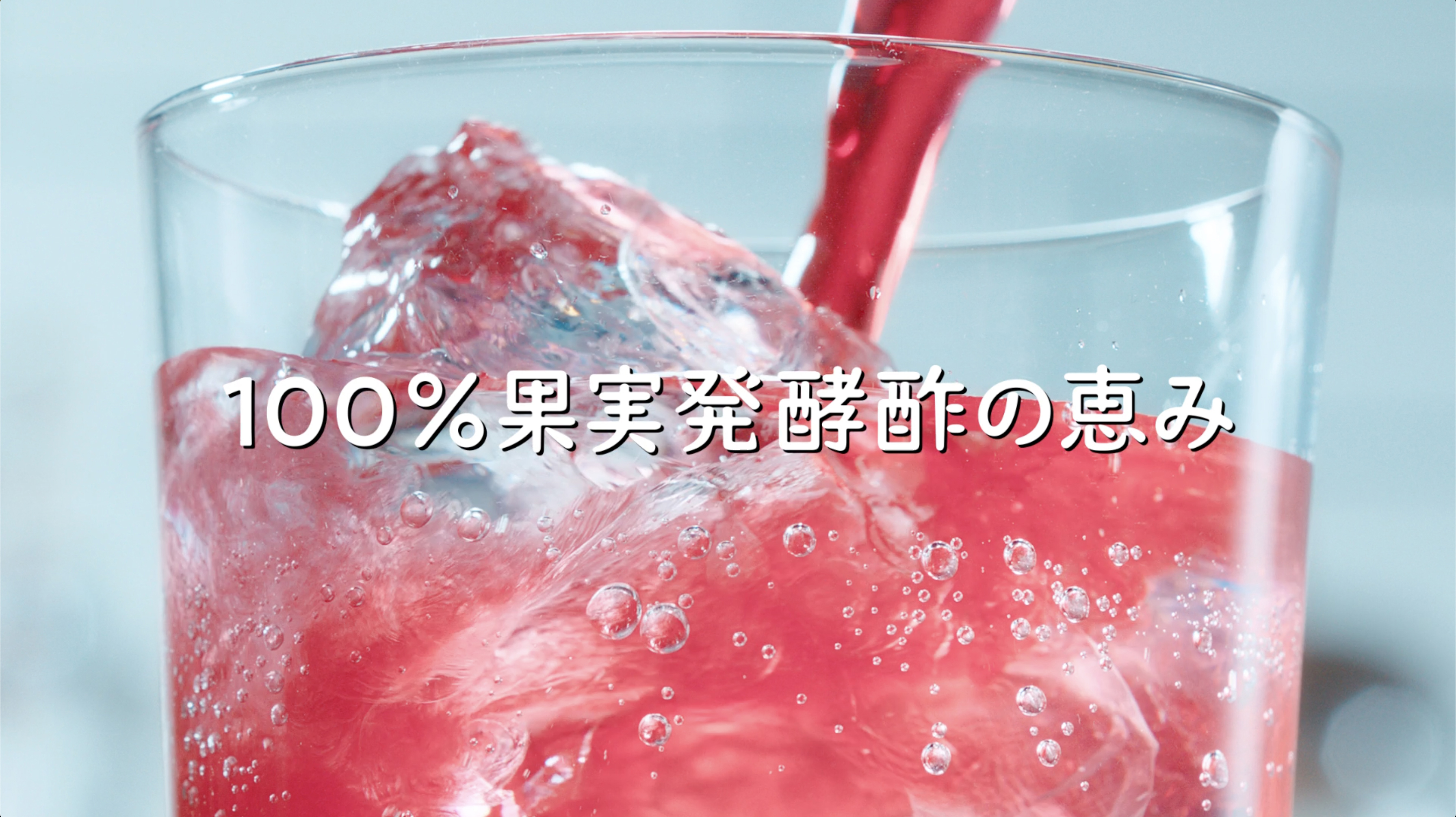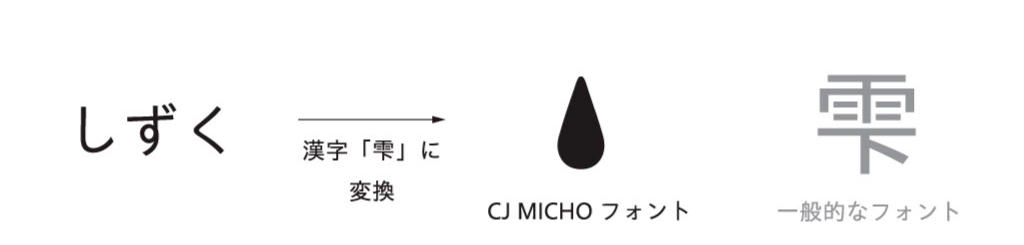
パッケージや広告デザインの
自由度が上がった!
ブランドの世界観を表現する
135文字のオリジナルフォント
韓国食品事業を展開するCJ FOODS JAPANのビネガードリンクブランド「美酢(ミチョ)」は、リブランディングプロジェクトの一環としてクリエイティブデザインを刷新し、2022年にオリジナルフォント「CJ MICHO」をモリサワと共同開発した。同社にとって初となるオリジナルフォントの制作過程、フォントの要件などについて、マーケティング部の担当者に伺った。
日本進出から10年を機にリブランディングのプロジェクトを始動
美酢は「100%果実発酵酢から作ったビネガードリンク」という、従来のお酢飲料とは全く異なるコンセプトで2011年に日本市場に進出した。それまで「味は二の次で、健康のために我慢して飲む」ものであり、中高年の男性が主な購買層だったお酢飲料のイメージを覆し、健康や美容を意識する若い女性を中心に支持を拡大。販路の多様化や積極的なマーケティング活動も、美酢ブランドの認知向上につながっている。
CJ FOODS JAPANは、日本で美酢の販売を開始してから10年が経過したのを機に、リブランディングのプロジェクトを始動。ターゲットである若年層に、身近さや美容面のベネフィットをさらに訴求するため、クリエイティブを刷新することになった。「改革というと大げさですが、今の時代に即したベストなデザインにしていこうという趣旨です」と、美酢のパッケージ、広告などのデザインを手掛けるマーケティング部 デザイン課係長の曺氏は語る。これまではデザインに既存のフォントを使用したり、またそれに既存のフォントをベースに作字した文字を組み合わせて使用したりしていたという。
韓国の本社(CJ第一製糖)が展開するナショナルブランドやグローバルブランドの多くは独自フォントを持ち、一貫性のある世界観を生み出している。CJ FOODS JAPANでは初の試みとなるが、美酢ブランドのオリジナルフォント開発は、プロジェクトの重要な柱として位置付けられた。
使用頻度が高い135文字をオリジナルフォントとして開発
共に開発を進める相手にモリサワを選んだのは、様々な雰囲気を持つフォント制作の実績があり、美酢ブランドにもっとも合うフォントの制作が期待できること、デザイン面のサポートの手厚さが大きな理由だった。「私もデザイナーですが、フォントデザインに関しては専門外です。要望を出したとしてもどこまでできるか、そもそも実現可能な要望なのか分からない部分もありました。しかし、モリサワさんは最初のご提案時から専門のフォントデザイナーさんが同席されていて、細かい要望や質問にもすぐに対応していただけたので、非常に安心感がありました」(曺氏)
曺氏が挙げた要件は、ブランドのシンボリズムが発揮されているか(象徴性)、小さな文字であっても可読性を保てるか(視認性)、印刷方法やデバイスを問わず、美しく表現できるか(汎用性)の3点。これを踏まえ、商品パッケージや広告、販促物での使用頻度が高い漢字・ひらがな・カタカナと記号の計135文字を、オリジナルフォントとして開発することになった。
視覚的な資料の活用でフォントイメージをつかみやすく
象徴性の部分について、「優しくカジュアルなこれまでの美酢の世界観は守りながらも、現代的なフレッシュさや活気をプラスしたかった」と曺氏は振り返る。フォントはコンマ数ミリの違いであっても文字を並べたときの印象が大きく変わり、抽象的な「イメージ」を具現化する難しさもそこにある。
「モリサワさんにデザインイメージとウエイトを4パターンずつ提案していただいたのですが、わずかな違いでも雰囲気が大きく変わるので、その繊細なニュアンスを楽しみながら選ぶことができました。さらに、パッケージに採用した場合どう見えるかをサンプルとして付けていただいたので、文字単体で見るよりも視覚的にイメージしやすく、非常に助かりました」(曺氏)。
ロゴとしても使用する漢字の「美酢」は、これまで親しまれてきたイメージを守るために従来の字形から大きな変更を加えていない。一方、ひらがなとカタカナは全体に丸みを持たせ、ふところを広く、重心は低く設計することで、可愛らしく親しみやすい印象となった。曺氏は「カタカナはロゴに入れる『ミチョ』のほか、フレーバー名などパッケージで小さく表示するケースもあります。今回は1種類のウエイトで依頼したのですが、印刷しても小さく使っても文字がつぶれず、かつきちんと読める太さなので、汎用性も高いと思います」と評価する。
「要件の3点をクリアしている上、フォントの完成度も高い。弊社のチームメンバーは、完成したフォントをとても気に入っています。可愛さだけでなく、美酢ブランド特有の感性までも表現できていると思っています」(曺氏)。
消費者と美酢をつなぐ「ミチョフォント」
チームメンバーが「ミチョフォント」と呼ぶ新フォント「CJ MICHO」は、すでにテレビCMに採用され、今後、ロゴや商品パッケージにも採用される。本格的な展開はこれからだが、オフラインの店舗販促物からウェブ広告、デジタルサイネージに至るまで幅広く活用する予定だ。
美酢ブランドのプロモーションを担当するマーケティング部 Michoグループの池田氏は「ミチョフォントの完成で、パッケージデザインの自由度が広がった」と笑顔を見せる。「身近にあって気軽に楽しめるカジュアルさや、時代に合った新しいフレーバーや商品で消費者を飽きさせないところ、果物の美味しさやカラフルな色合いを表現したワクワクするデザイン。これらは美酢ブランドのアイデンティティーであり、われわれがもっとも大切にしているものでもあります。例えば、商品は最初900mLの希釈タイプのみの展開でしたが、健康・美容への関心の高まりや食生活の多様化に合わせて、2018年からはストレートタイプを始め、ゼリー飲料、アルコール飲料、アイスなど商品ラインナップを充実させています。商品の種類によって少しずつ雰囲気も変わるのですが、ミチョフォントを使用することによって、通底する世界観が表現できることを期待しております」(池田氏)。